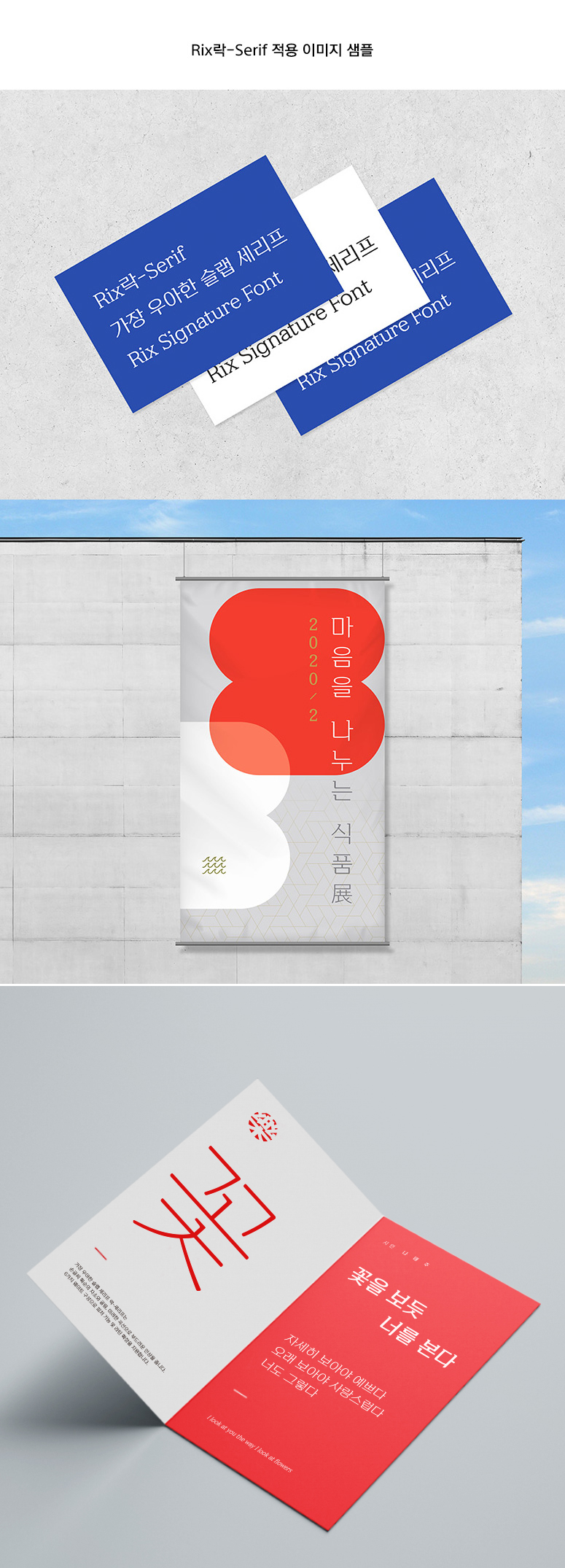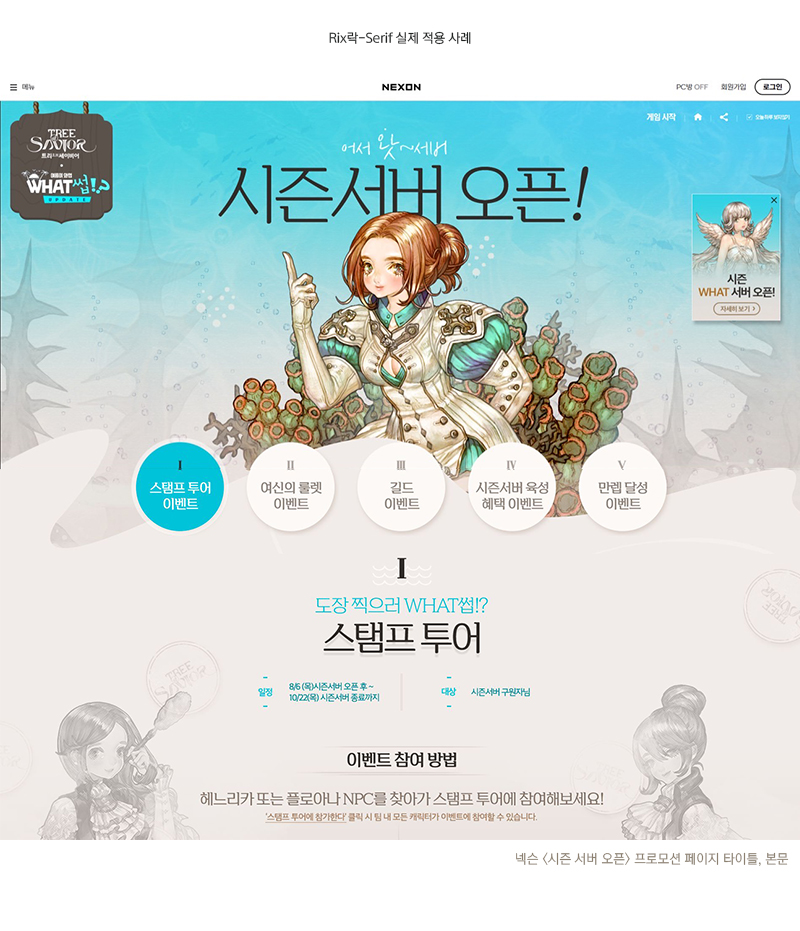
Rix락-Serif
6 종 - Heavy, Extra Bold, Bold, Medium, Light, ThinRix락-Serif는 꽉 찬 골격과 슬랩 세리프가 강인하면서도 미려한 이미지를 자아내는 서체입니다.
손글씨 획순과 굴림 사용으로 편안하고 안정적이며, 단단한 뼈대와 우아한 획의 조화가
중성적인 성격을 가져 다양한 분야에 범용 될 수 있습니다.